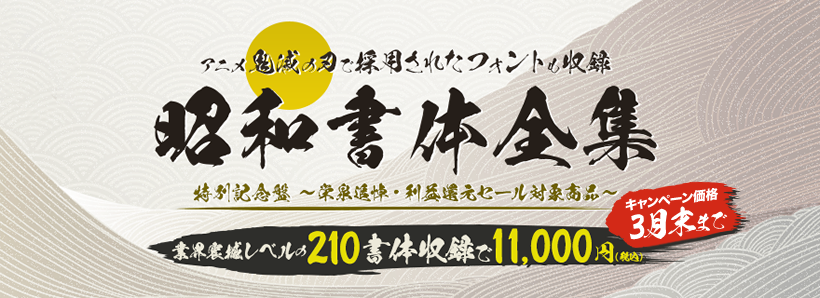
本格手書き毛筆書体メーカー『昭和書体』の全210書体を収録した「昭和書体全集」。
アニメ「鬼滅の刃」で採用された「闘龍書体」「陽炎書体」も収録しています。
収録書体 毛筆和文フォント 92書体(菩薩書体 9書体、社外書家書体 3書体、基本書体+高解像度書体+デザイン書体 53書体、爽シリーズ 27書体)
梵字フォント 4書体
欧文フォント 114書体
計 210書体
毛筆和文フォント